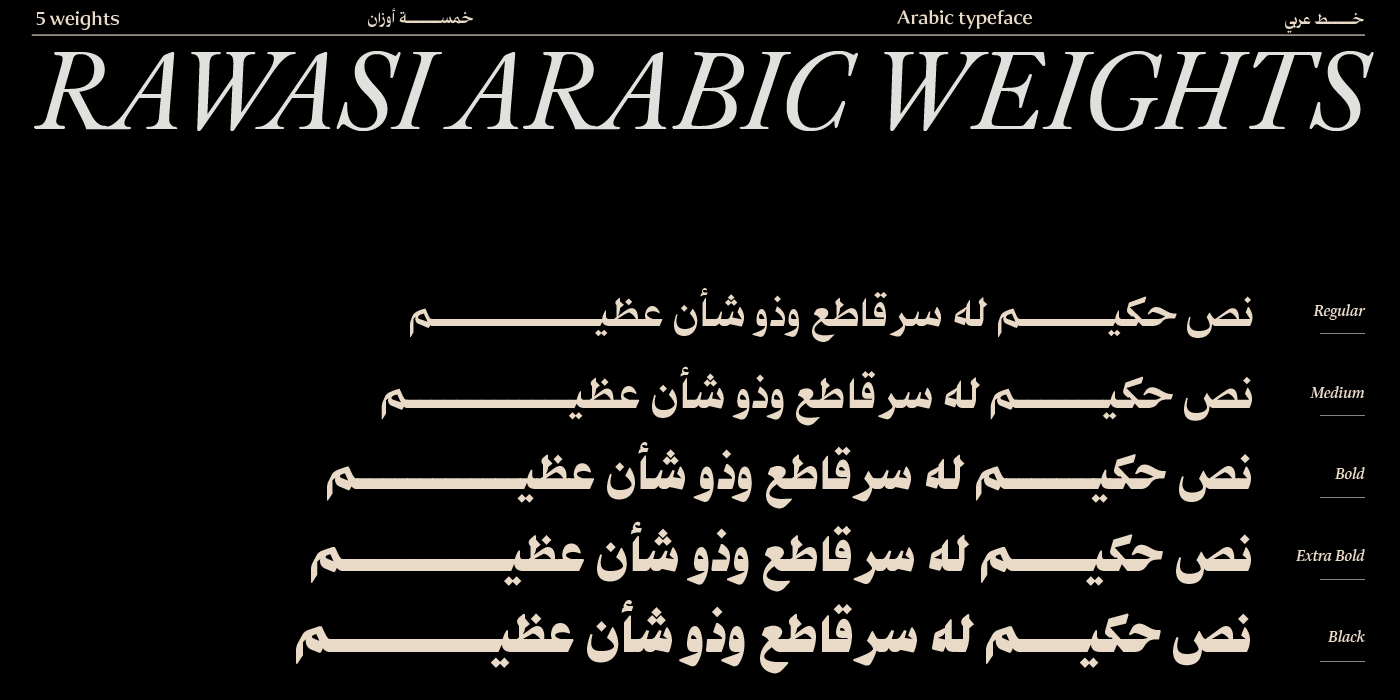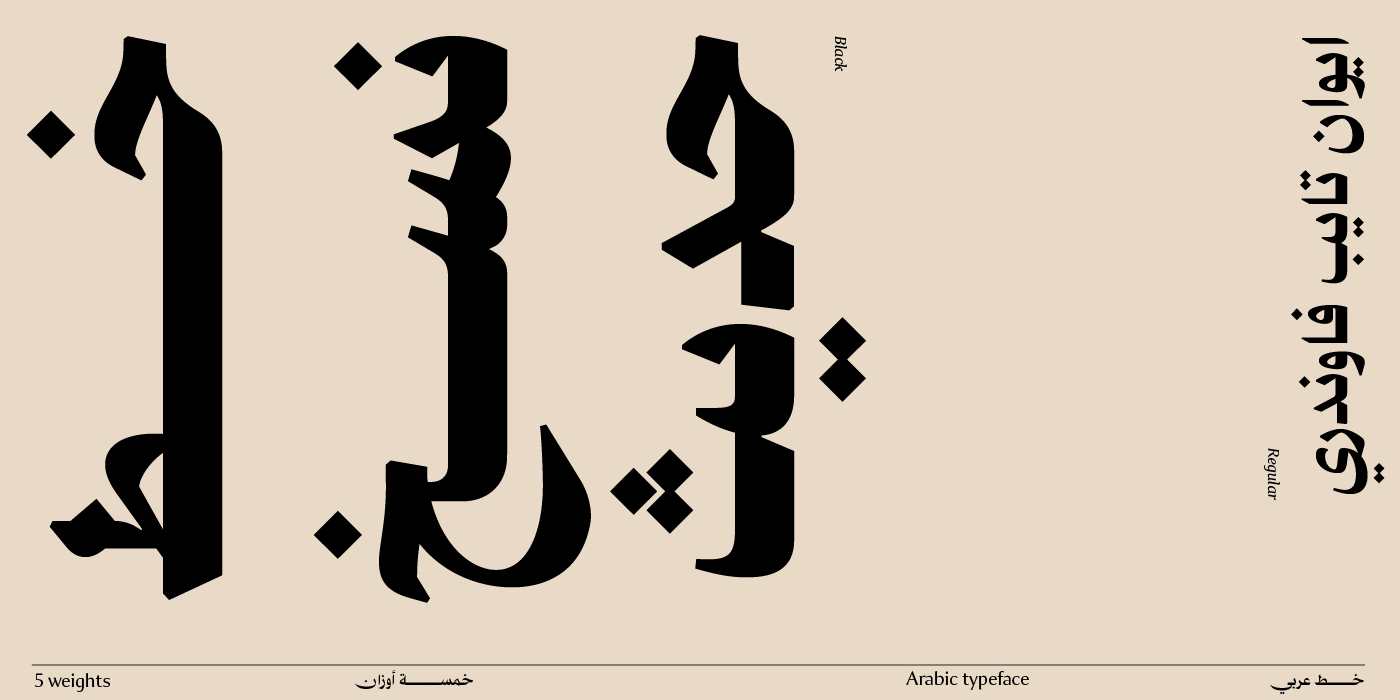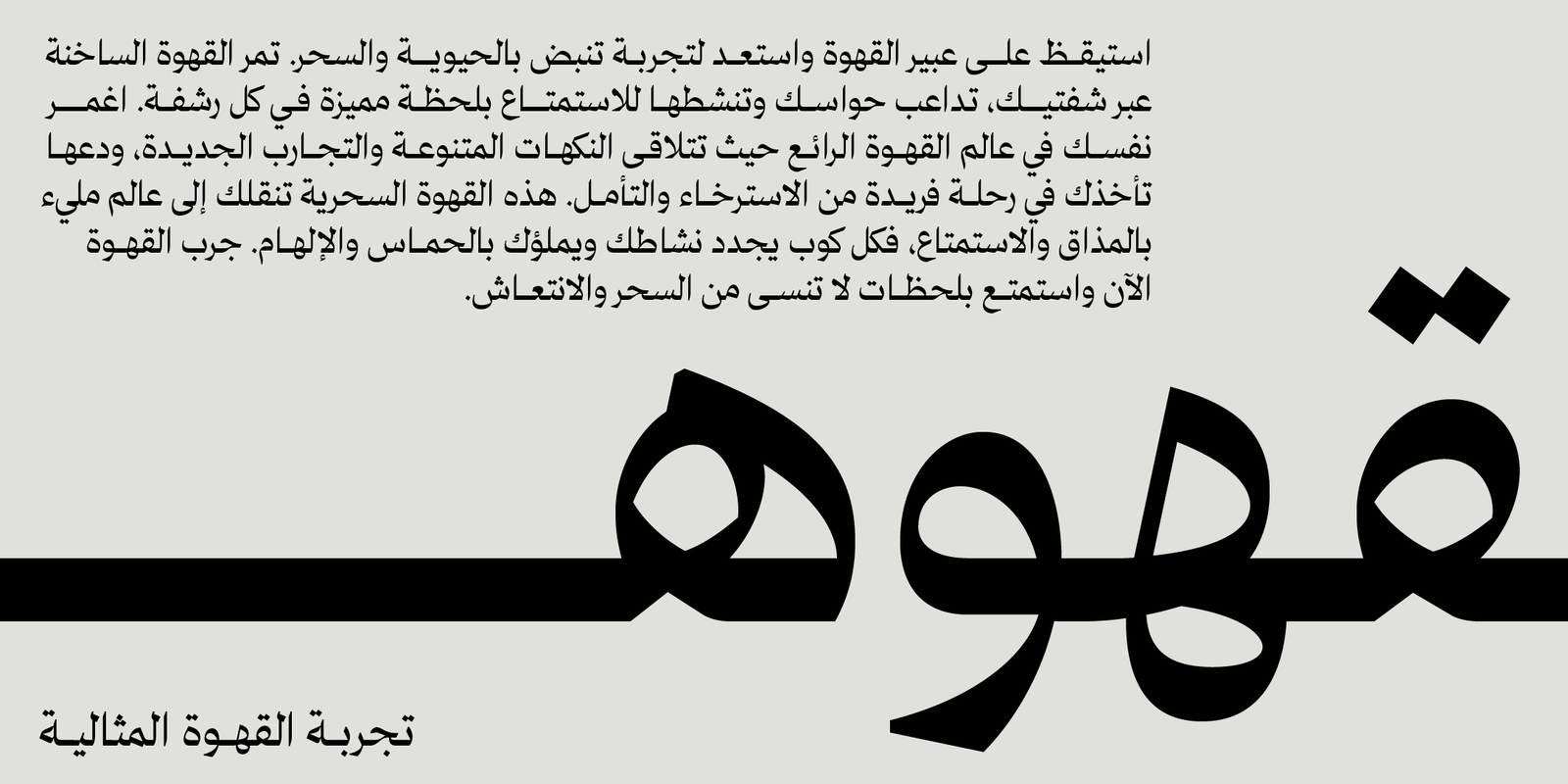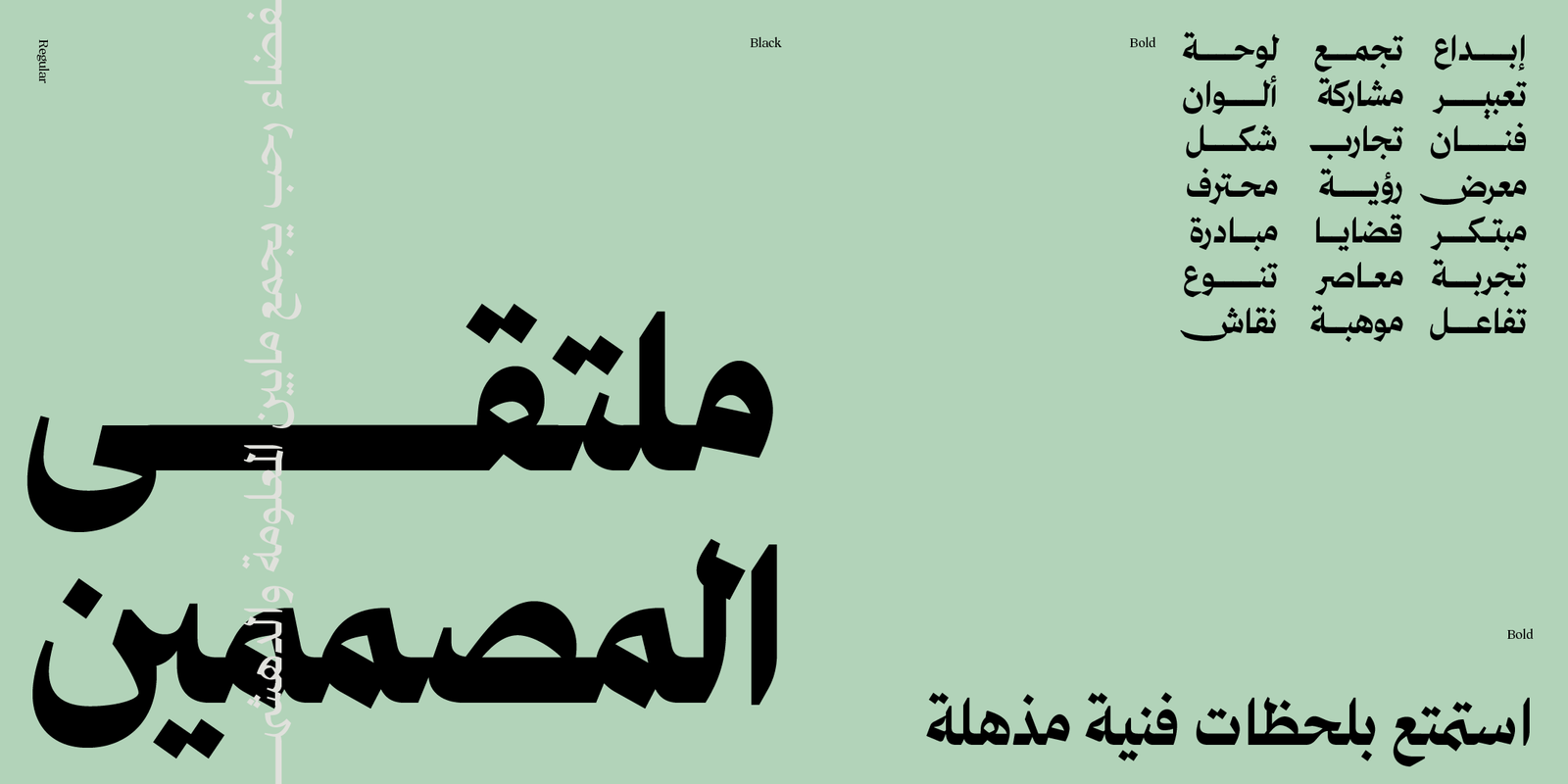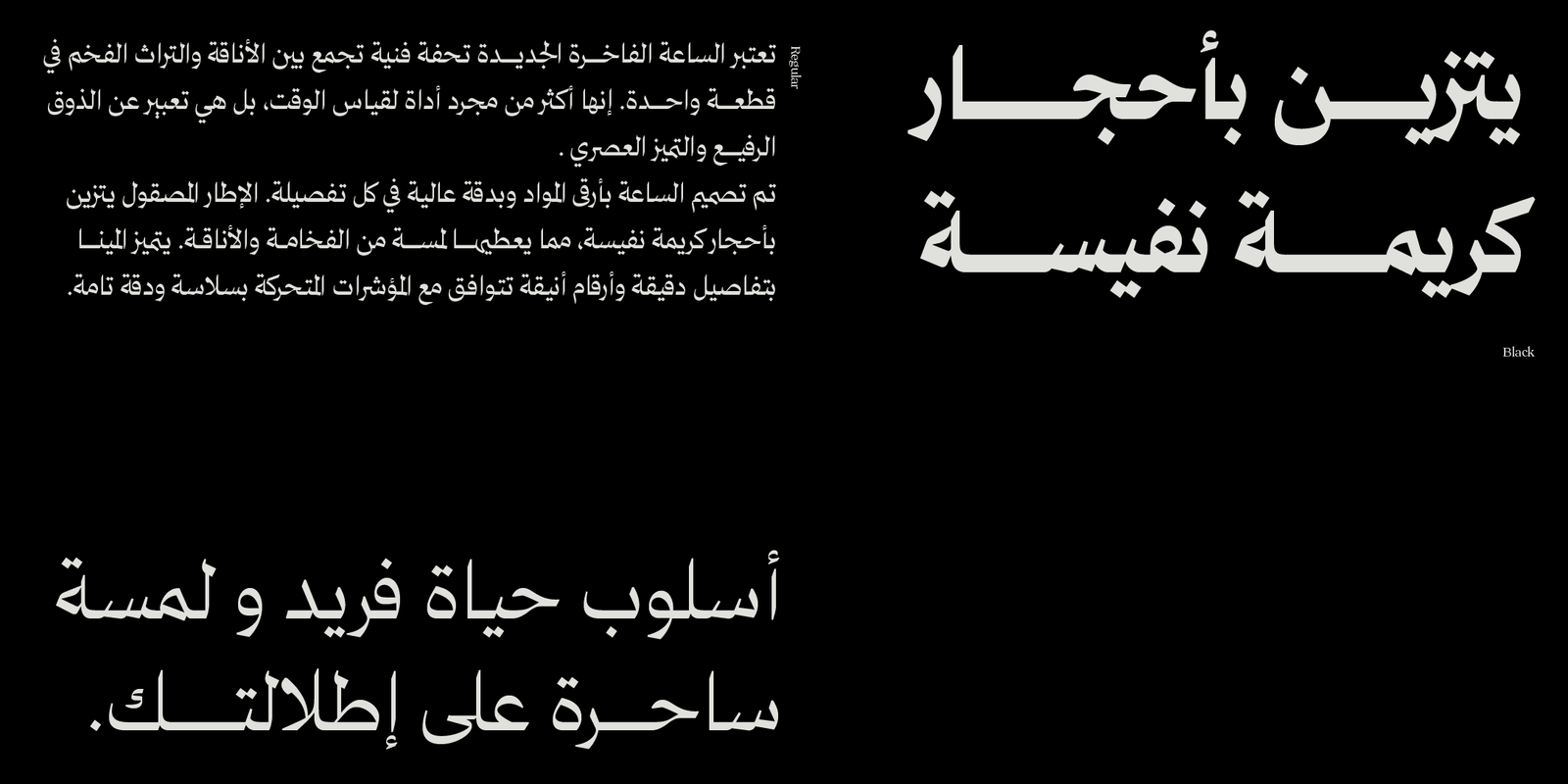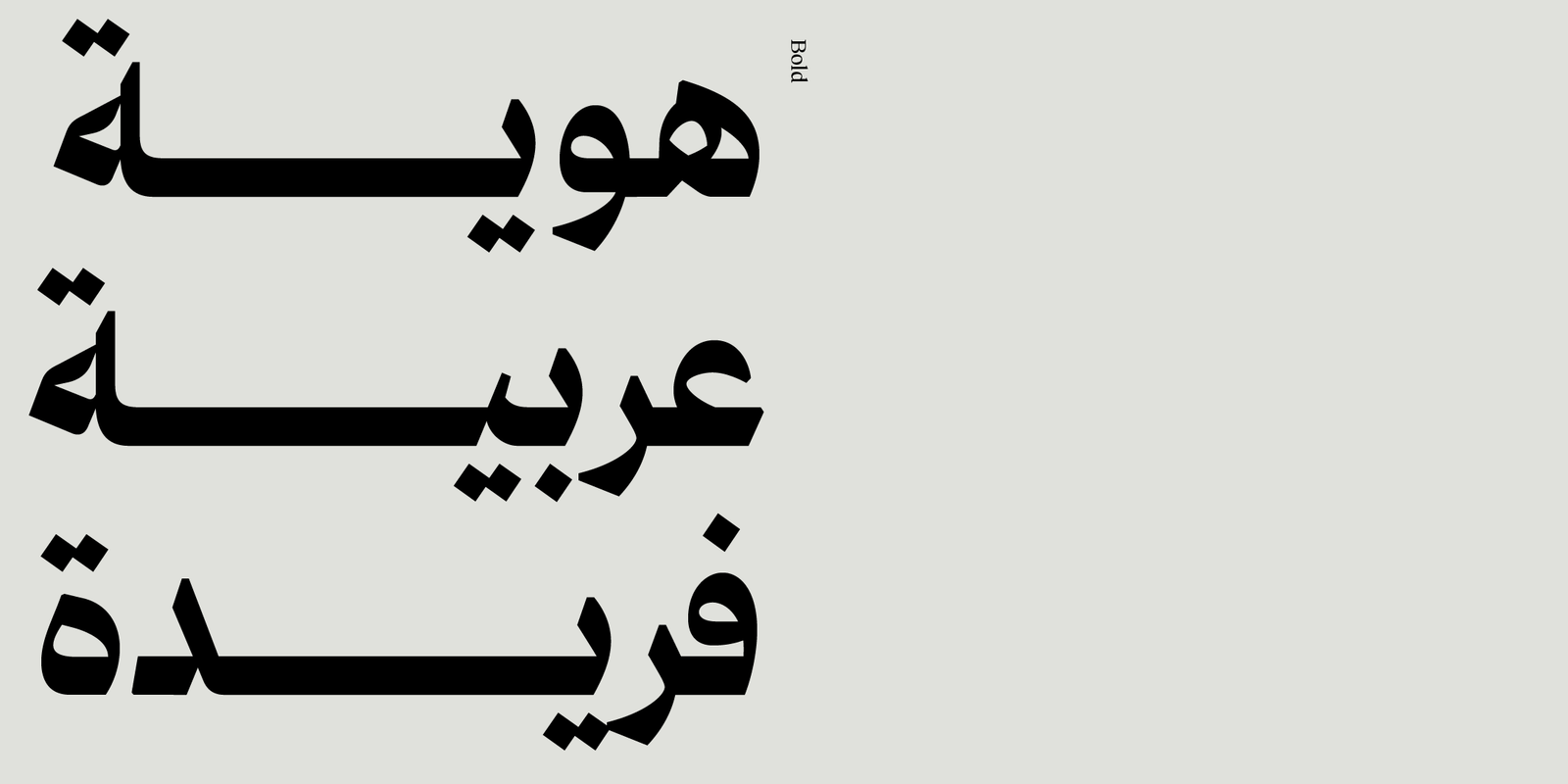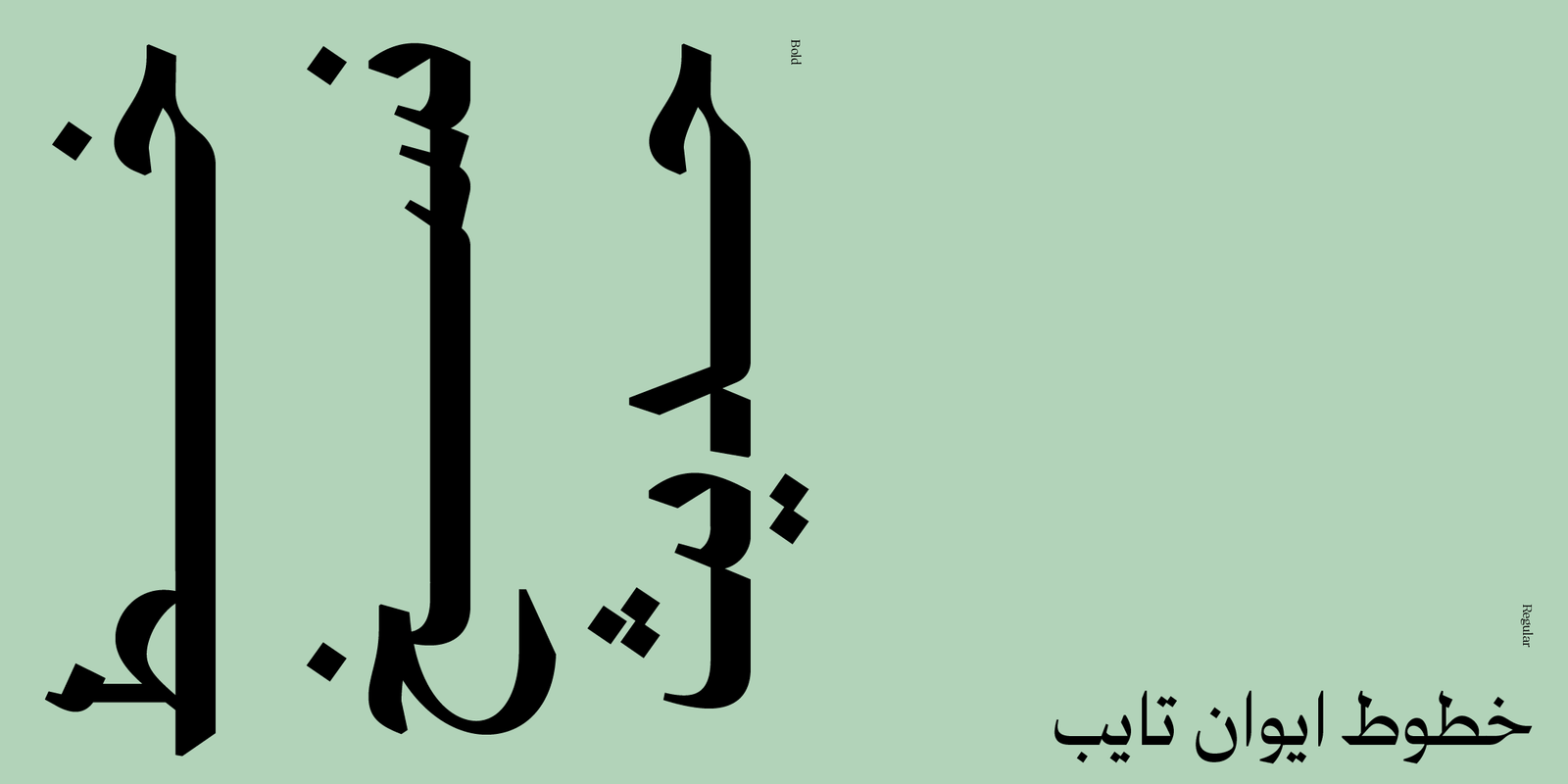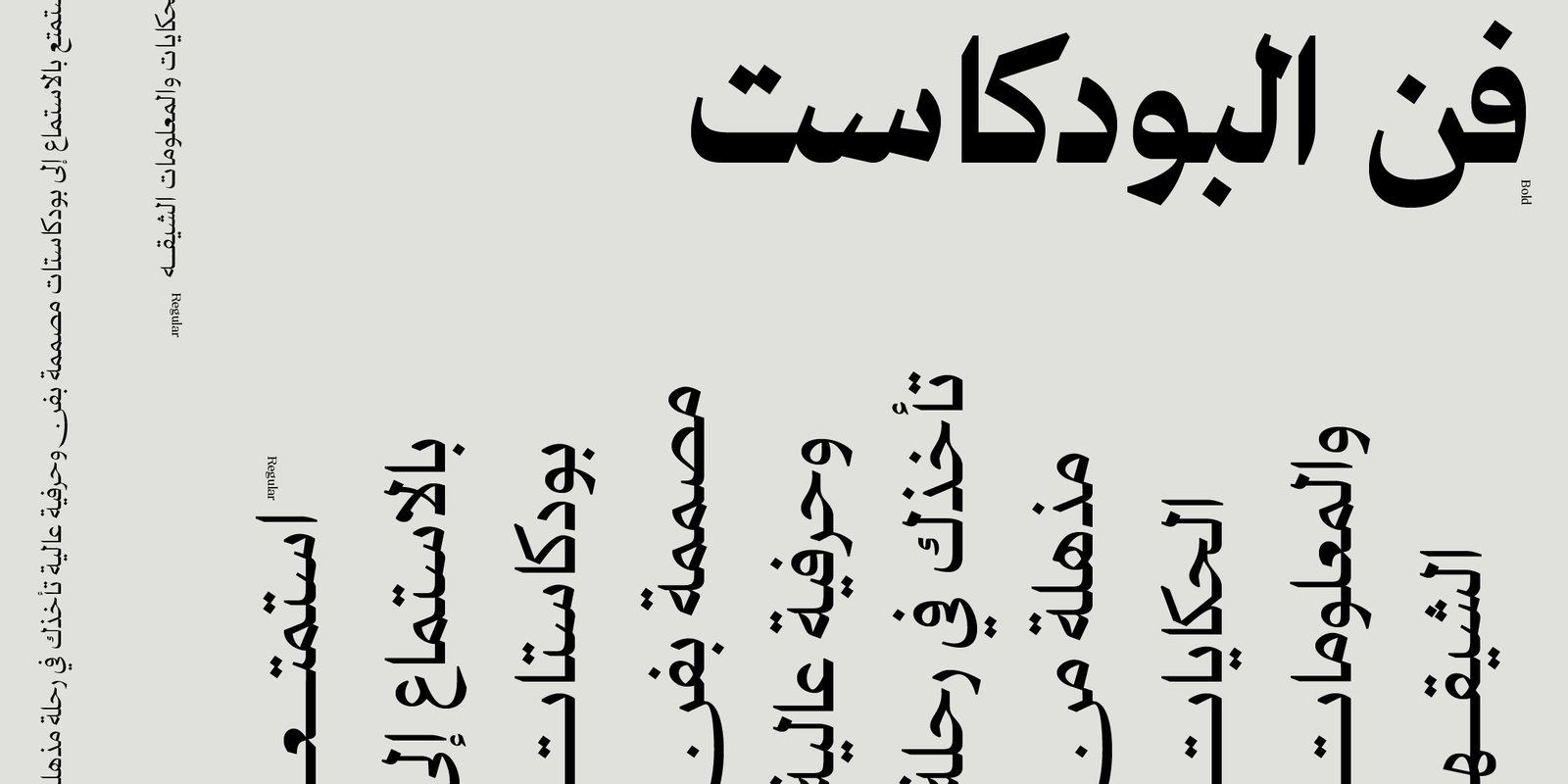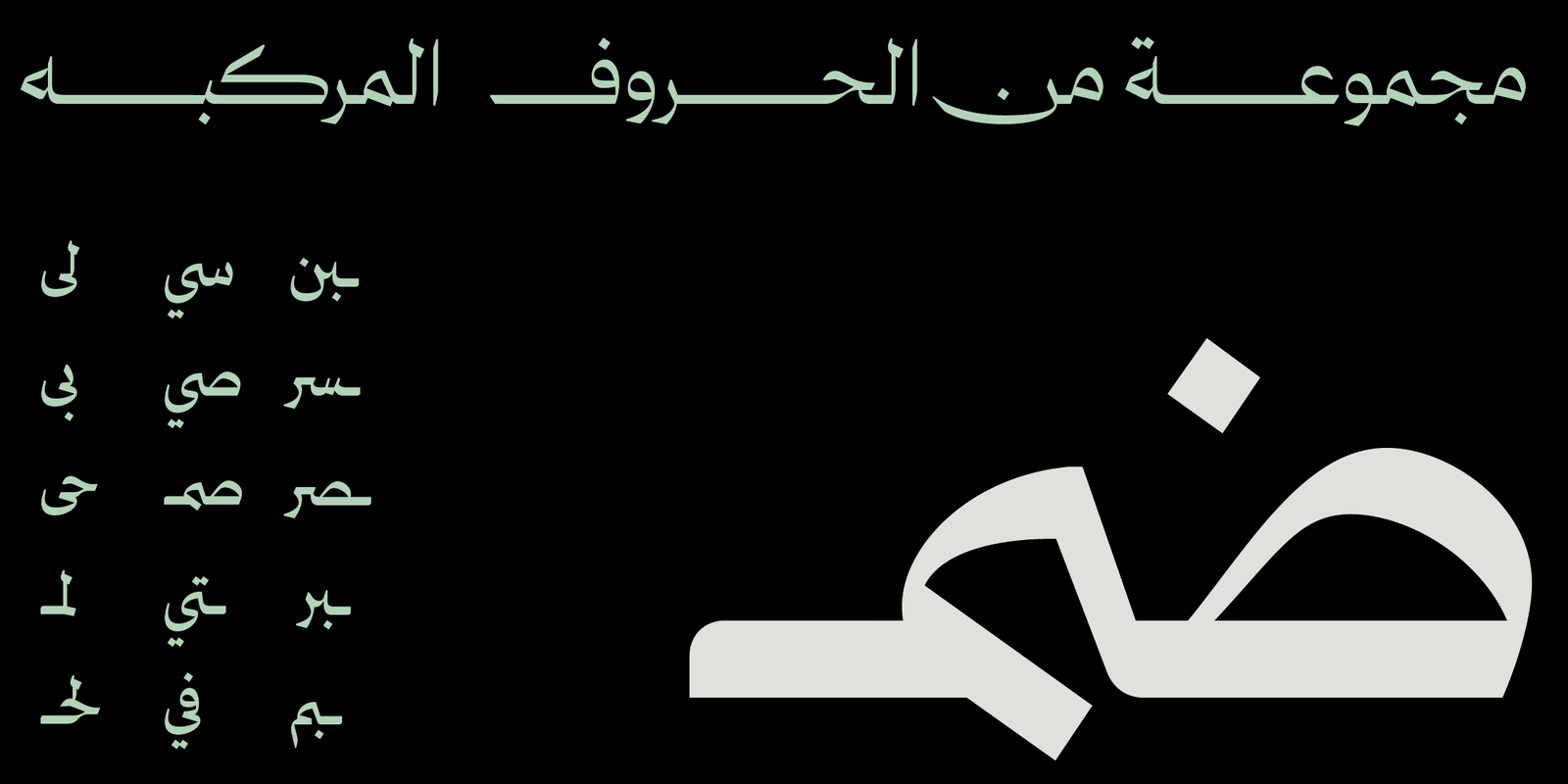
Rawasi Arabic typeface – خط رواسي
Rawasi Arabic Typeface – خط رواسي العربي
رواسي عربي هو خط عربي احترافي مستوحى من النسخ المسطري ، يتميّز بتصميم قوي وحواف حادة تمنحه حضورًا بصريًا واضحًا ومؤثرًا.
يضم الخط 7 أوزان متكاملة توفّر مرونة عالية في الاستخدام عبر مختلف المشاريع، من الشعارات والهويات البصرية إلى المواقع والتطبيقات والمطبوعات.
يجمع رواسي بين وضوح القراءة، الانضباط الهندسي، والأناقة الحديثة ليكون خيارًا مثاليًا للتصميم التجاري والمؤسسي.
Rawasi يمنح أعمالك طابعًا احترافيًا متوازنًا بين الجمال والقوة.
مميزات خط رواسي :
يتضمن الخط العديد من مزايا OpenType التي تضفي عليه مرونة وتنوعًا في الاستخدام، مثل:
• أحرف مرسلة (تُفعَّل بإضافة “ءء” بعد الحرف)
• أحرف مركّبة تُحسّن سلاسة التراكيب وتناسق النص.
• يدعم رمز الريال السعودي والريال العُماني ،ويتم تفعيلهما تلقائيًا عند كتابة الاختصارات: ر.س للريال السعودي ر.ع للريال العُماني
الاوزان :  سبعة أوزان
خط رواسي للعناوين